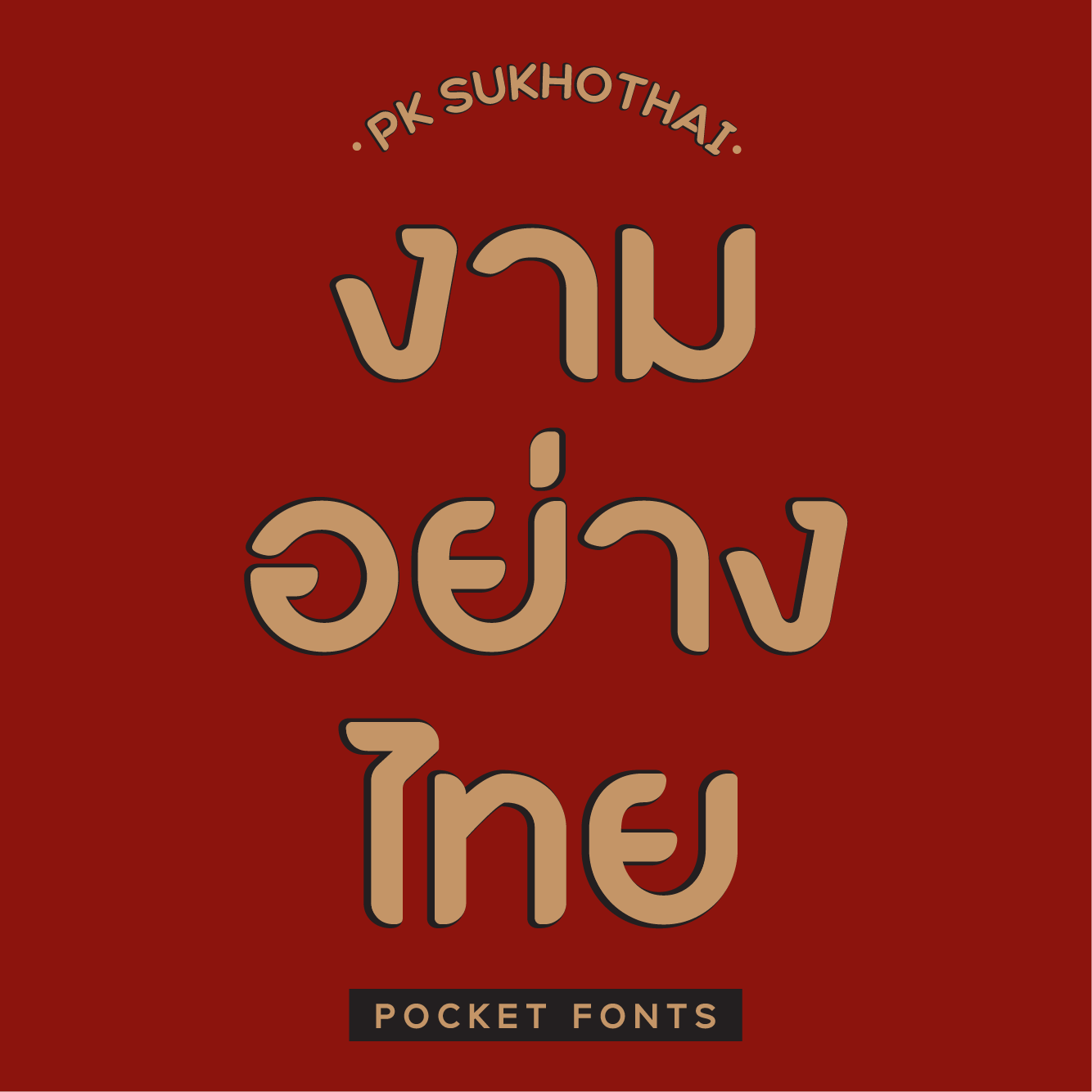
PK Sukhothai
Pocket Fonts
PK Sukhothai l พีเค สุโขทัย
ฟอนต์ PK Sukhothai ผสมผสานความโมเดิร์นทันสมัย แบบ Latin รวมกับความเป็นไทยด้วยปลายที่แหลมและเอียงไปด้านนึงคล้ายกับลักษณะการเขียนอักษรไทยแบบอาลักษณ์ ผสมผสานกันอย่างลงตัว